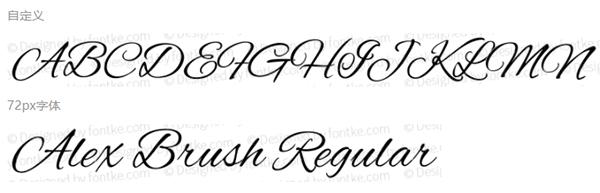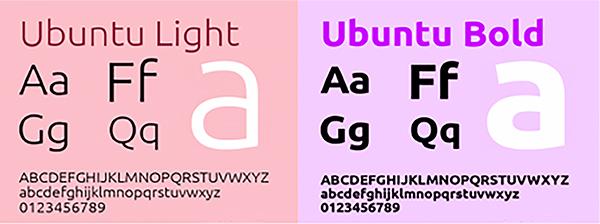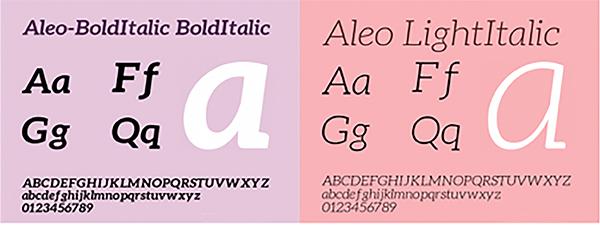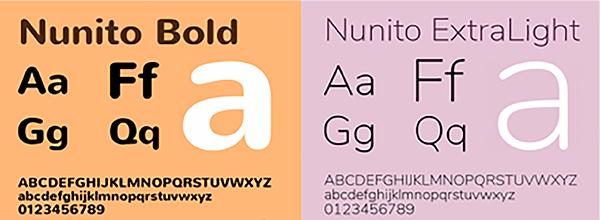
我们经常会在网上浏览或者在街上的店面看到很多很好看的英文字体,但苦于不知道怎么查找,而且也怎么会英文,所以导致经常想要下载使用这些字体却没有什么好办法。还有就是找到了自己想要的,认为好看的英文字体,想要作为商业用途,如作为店面商标,作为广告图片等,但是又不知道是否能够免费商业使用。现在我为大家介绍一些可以免费使用(包括商业用途)且好看的英文字体,都是干货!通通都带走吧!
Alex Brush 字体
这款字体的话想必大家可能不陌生,这款字体算是属于国内的一款挺火爆的英文字体了。对于它的书写风格的话是一个优美流畅的毛笔写作。它有短的上升和下降,且与其它字体中相比却有不一样的易读性。
AiDeep 字体
AiDeep个人认为它的结构都是很细致的,且有点强硬的风格,也是非常火爆的一款字体,是由网络尖刀用户体验中心UED团队出品的一套由公司品牌命名的开源字体,仅收录了26个英文大写字母、及26个英文小写字母、还有从0到9这10个常用阿拉伯数字。
Grand Hotel 字体
这款字体的话让人感觉有种老派的艺术气息,据说Grand Hotel字体创作的灵感来自于1937年由Tyrone Power主演的电影《大都市咖啡馆》的片头画面,带有着里面电影的某些情节的感觉,同样也是相当的受欢迎。
FIFA Welcome 字体
这款字体虽没有像其他的那么的火,却是个人最爱的英文字体之一,个人觉得这款字体的风格没有过分的也没有过于拘谨,是属于“点到为止“的那种感觉,所以个人也是强烈的推荐吧。
Pacifico
Pacifico同样也是让人有一种老派艺术的气息,由Vernon Adams创造,里面总共有233个字符。
Samba 字体
Samba的字体让人的感觉是有赋予了生命一样,每一个英文字都感觉有着无限的活力且带着搞怪的气息。
ZCOOL Addict Italic 字体
ZCOOL Addict Italic]中文称为站酷意大利体是由大猫Addict设计,站酷冠名的首款公益西文字库, 是可免费商用的西文字,2016年5月发布第一版。共包含52个字母,10个数字,24个符号。免费授权全社会使用。
Great Vibes 字体
曾有人这样评价过这个字体:”伟大的艺术都是由人创作的。足以表达这个字体的地位和观赏性。
一. Ubuntu类字体
Ubuntu类英文字体可以免费商用的有Ubuntu bold字体,Ubuntu boldlta字体,Ubntu Condensed字体,Ubuntu light字体,Ubuntu medium字体,Ubntu Mono bold字体等。
二. Akrobat类字体
Akrobat类英文字体可以免费商用的有Akrobat ExtraBold字体,Akrobat ExtraLight字体,Akrobat SemiBold字体等。
三. Aleo类字体
Aleo类英文字体可以免费商用的有Aleo BoldItalic字体,Aleo Light Italic字体,Aleo Regular字体。
四. Gentium类字体
Gentium类字体可以免费商用的有Gentium Book BasicBI字体,Gentium Book Basic B字体,Gentium Book Basic I字体,Gentium Book Basic R字体。
五. IBM类字体
IBM这类字体想必大家同样也是不陌生的,它也是在世界各地很流行的一种字体,可以免费商用的字体有IBM Plex Mono字体,IBM Plex Mono Bold字体,IBM Plex Mono ExtraLight Italic字体,IBM Plex Mono SemiBold字体,IBM Plex Mono Text Italic字体, IBM Plex Mono Thin字体,IBM Plex Sans Italic字体,IBM Plex Sans Medium Italic字体,IBM Plex Sans Text字体,IBM Plex Sans Thin Italic字体,IBM Plex Serif ExtraLight字体,IBM Plex Serif Italic字体,IBM Plex Serif Thin字体。
六. Jura类字体
Jura类字体可以免费商业使用的字体有Jura Bold字体,Jura BoldItalic字体,Jura Regular字体。
七. Merriweather类字体
Merriweather类字体可以免费商用的字体有Merriweather Black字体,Merriweather Bold字体,Merriweather Italic字体。
八.Montserrat类字体
Montserrat类字体可以免费商用的字体有Montserrat Alternates BlackItalic字体,Montserrat Alternates Bold字体,MontserratAlternates BoldItalic字体,Montserrat Alternates ExLight字体,Montserrat Alternates ExtraBold字体,Montserrat Alternates Italic字体,Montserrat Alternates字,Montserrat ExtraBold字体,Montserrat Regular字体。
九. Nunito类字体
Nunito类字体可以免费商业使用的有Nunito Bold字体,Nunito ExtraLight Nunito Regular字体, Nunito SemiBold字体。
十. Raleway字体
Raleway类字体可以免费商用的有Raleway Black字体,Raleway Black Italic字体,Raleway Bold字体, Raleway ExtraLight字体,Raleway Medium字体,Raleway SemiBold Italic字体。